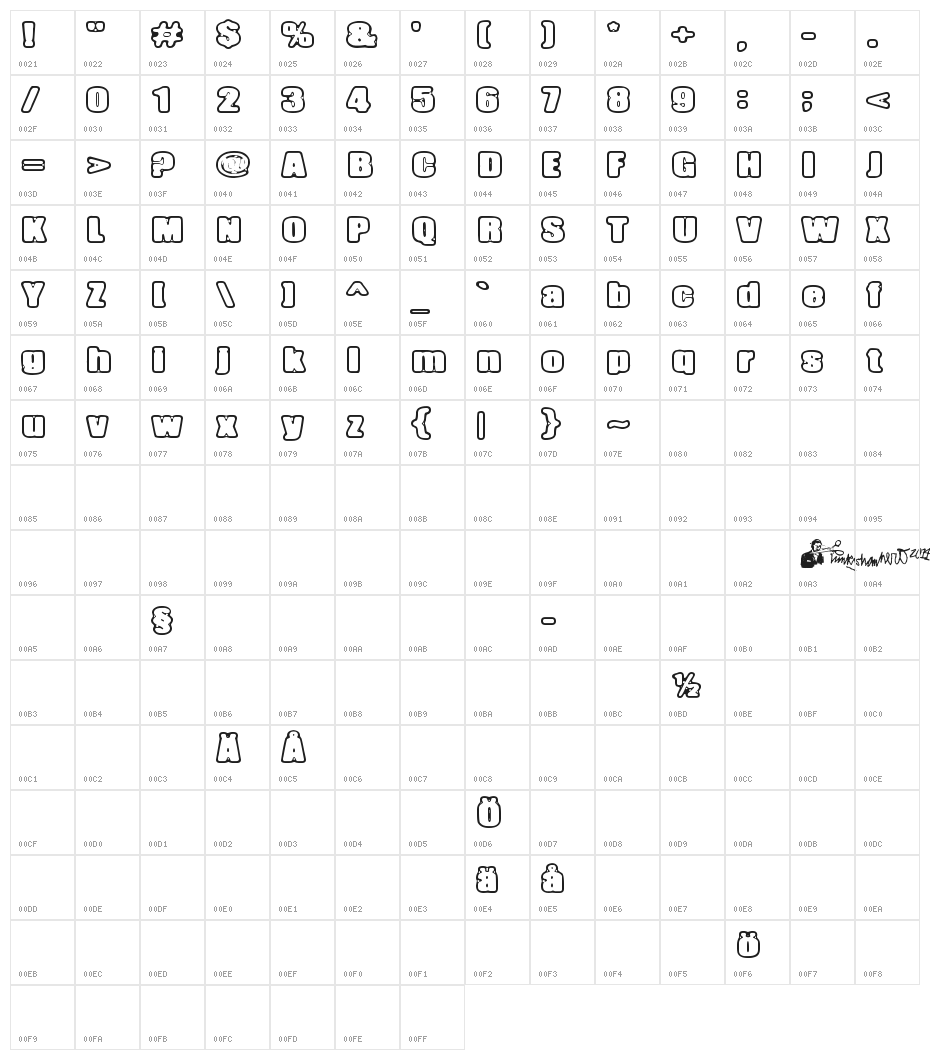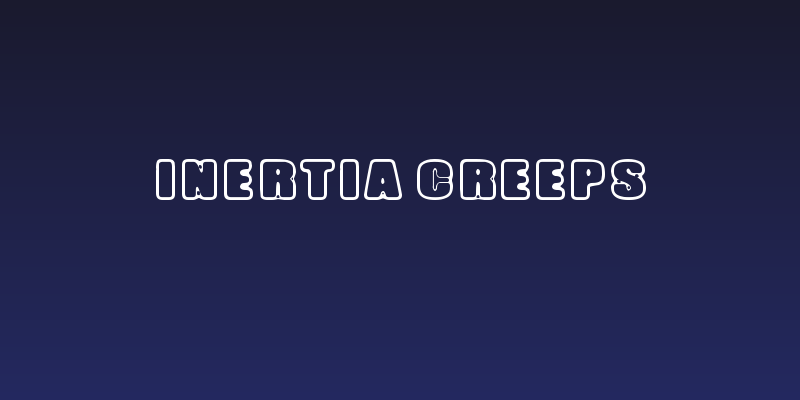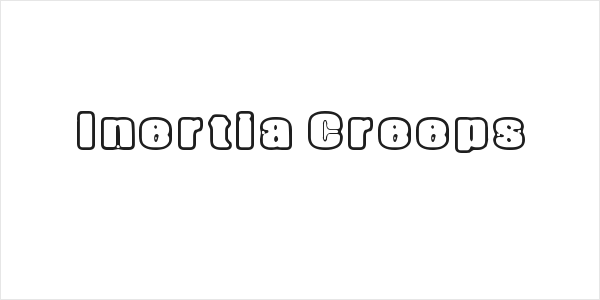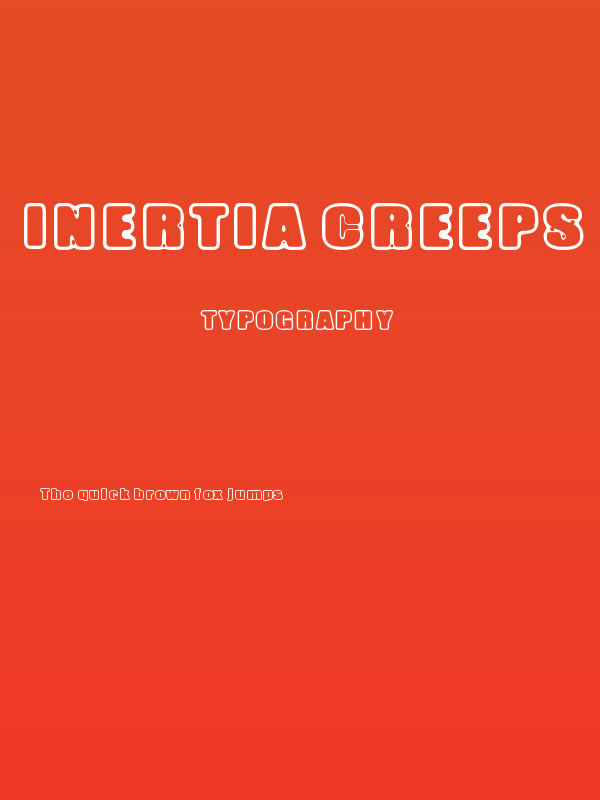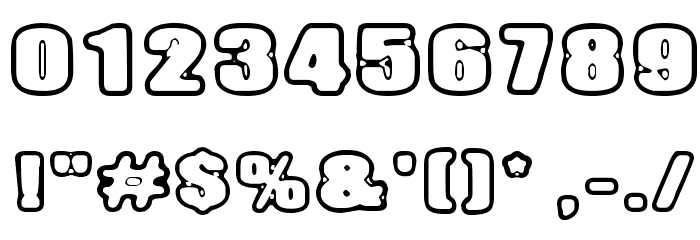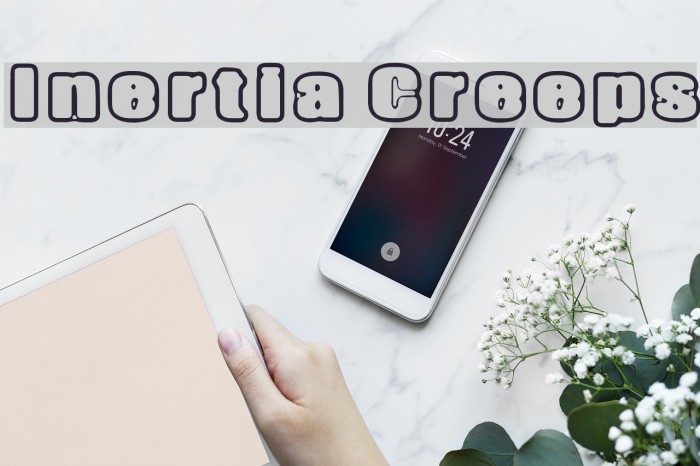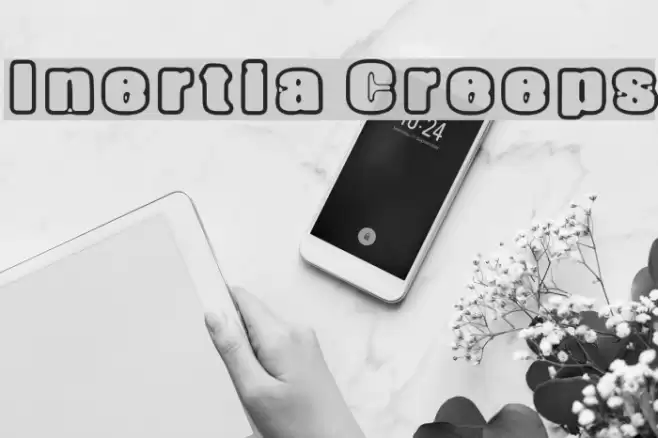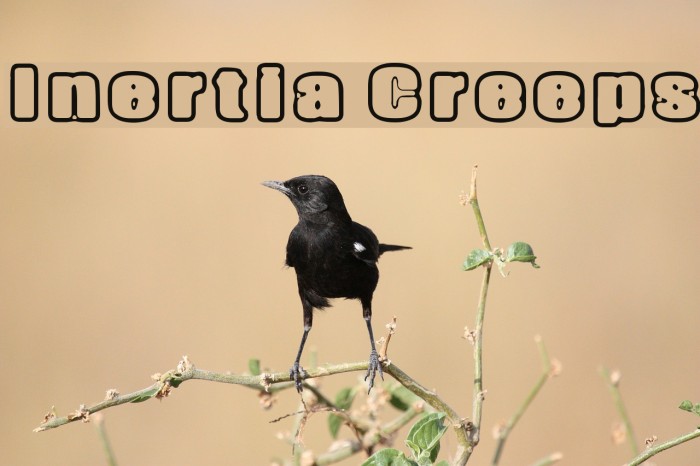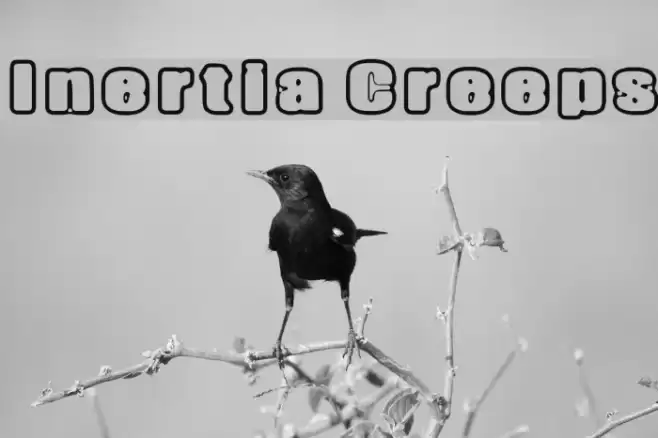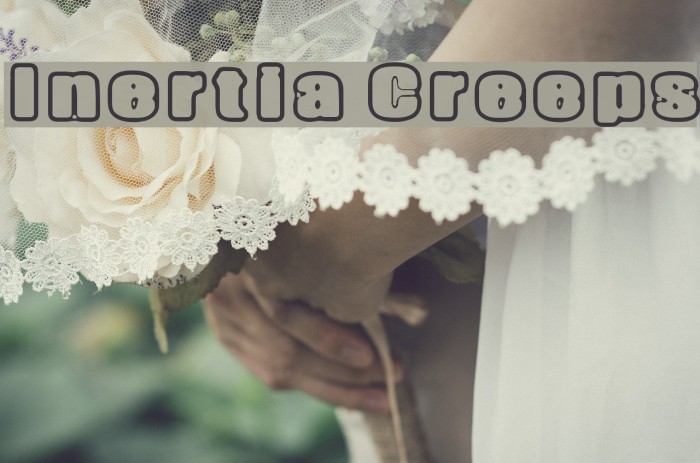
Inertia Creeps Font
✎ Distorted Eroded
| カテゴリ | Distorted Eroded |
| 全体的なスタイル | Urban, Edgy, Graffiti |
| 用途 | Logos, Posters, Album Covers |
| おすすめプロジェクト | Ideal for urban-themed posters, streetwear branding, music album covers, and edgy graphic designs. |